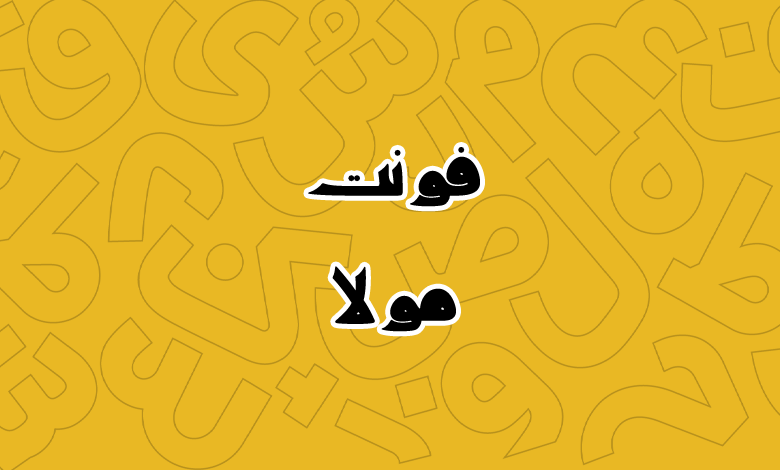
فونت مولا (Mola)
فونت مولا (به انگلیسی: Mola) قلمی به سبک نوشتههای تاریخی قدیمی است که میتوانید از آن در پروژههایی که نیاز به فونت عنوان در موضوعات تاریخی، فرهنگی و هنری، مذهبی یا عناوین کتاب و مجلات دارید استفاده کنید. در ادامه با دانلود فونت مولا با شما همراه هستیم.
این فونت که از زبان فارسی و عربی پشتیبانی کاملی دارد، توسط حسین زاهدی طراحی شده است که از دیگر کارهای وی میتوان به فونت نستعلیق برای کپ کات اشاره کرد. این فونت دارای سبکی فانتزی و با ظاهری کاملا نمایشی است.
در فونت فارسی رایگان مولا شاهد یک وزن معمولی Regular هستیم که حروف دارای سبک طراحی نمایشی هستند. از این جهت که ظاهر حروف یکسان نبوده و از طرفی دیگر چشمیها بهقدری ریز هستند که بهسختی در اندازههای بزرگ قابل تشخیص هستند.
در این فونت همچنین ظاهر حروف به شکل کلی تغییر داده شده است. بهعنوان مثال حرف «ی، ر، س، ش» که در تصویر زیر نیز نمونه آن را میبینید تغییرات کلی داشته است. این تغییرات به شکلی است که شاید یک نوجوان هم نتواند بهدرستی برخی حروف را تشخیص دهد.
- پروژههایی که نیاز به فونت عناوین دارید.
- استفاده برای کارهای تاریخی همچون کاور تصویری یا متن ویدئوها.
- استفاده برای کارهای فرهنگی و هنری مرتبط با ادبیات.
- استفاده در کارهای مذهبی که مرتبط با تاریخ هستند.
- استفاده برای عنوان کتاب و مجلات.
- استفاده برای چاپ بنر و بیلبوردهای بزرگ با موضوعات تاریخی، فرهنگی و هنری.
فونت Mola از زبان انگلیسی پشتیبانی نمیکند و فاقد گلیف برای این زبان است. اما در مقابل زبان فارسی و عربی را بهجز بخش اعداد «۰۴۵۶» به شکل استاندارد پشتیبانی میکند.
اگر مایل به استفاده از این فونت برای سایت هستید، میتواند برای اسلایدر در فروشگاههای اینترنتی یا سایتهای محتوایی با موضوعات تاریخی، فرهنگی و هنری مناسب باشد. چرا که ظاهری نمایشی دارد و مخاطب را جذب میکند.